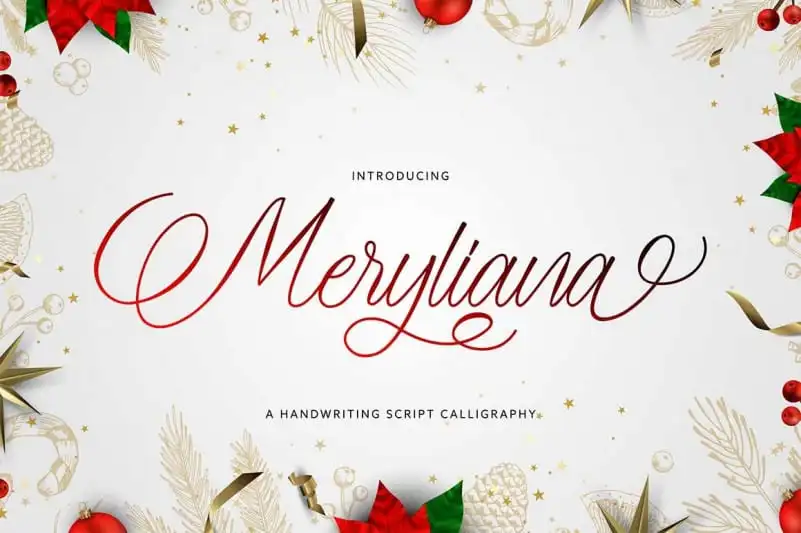
A Meryliana Calligraphy Font é uma bela tipografia moderna que imita a arte de escrever à mão com todos os seus defeitos e beleza. Desenvolvida pelo JunCreative, ela combina elementos orgânicos e elegantes para criar um estilo clássico e sofisticado. Esta fonte perfeita para o branding, projetos, logomarcas, casamentos, cartões de apresentação, postagens nas redes sociais e anúncios também é ideal para qualquer projeto extraordinário que você possa ter em mente. Com uma tipografia clássica e moderna, a Meryliana Calligraphy Font oferece alternativas sofisticadas que tornam-a perfeita tanto para uso pessoal quanto profissional. Suas linhas sutis e curvas suaves criam um estilo de escrita elegante e arrojada que se adapta perfeitamente à necessidade específica de cada projeto, seja uma marca empresarial inovadora ou um cartão de presente romântico. Com a Meryliana Calligraphy Font na sua biblioteca de recursos gráficos, você pode criar design e identidade visual com estilo. Seja para estabelecer uma conexão emocional com seu público-alvo ou para tornar suas mensagens mais memoráveis e impactantes, essa fonte é um excelente recurso. Não hesite em explorá-la para transformar seus projetos digitais em obras de arte únicas.